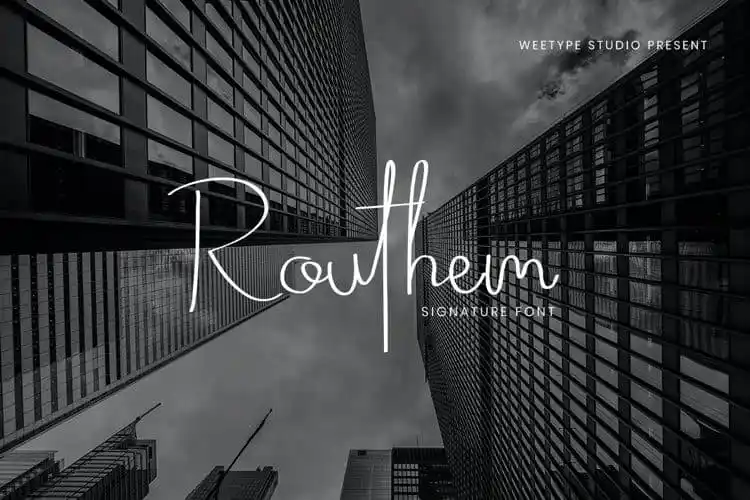
Routhem Handwritten Font – Download Grátis
A Routhem Handwritten Font é uma elegante tipografia script que enriquece qualquer projeto editorial ou design gráfico. Sua sofisticação única faz dela uma escolha inteligente para qualquer profissional de design que busca um estilo atraente e sofisticado. Esta fonte foi criada por Weetype Studio, uma equipe dedicada à desenvolver tipos de letra premium. Com suas curvas elegantes e seu fluxo suave e inebriante do papel, Routhem é perfeito para dar vida ao design gráfico com um toque refinado que destacará qualquer texto. Esta fonte script, disponível no formato Script Fonts por designer 99designs, é uma paixão de muitos profissionais de design, pois oferece a autenticidade e a sofisticação necessárias para criar designs memoráveis e imprimíveis.